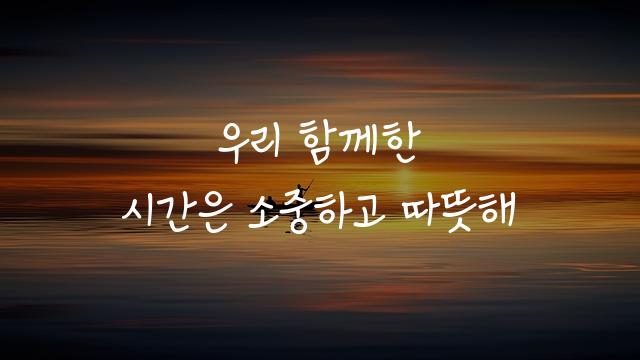
교보손글씨 2022 김혜남은 교보문고에서 제작한 어른 손글씨 폰트로, 세련되고 친근한 인상을 주는 디자인입니다. 이 폰트는 전통적인 손글씨의 감성을 현대적으로 재해석한 특징을 가지고 있습니다.
교보손글씨 2022 김혜남은(는)
손글씨, 감성적인, 부드러움 계열의 생김새를 가지고 있으며
초대장, 인사말 카드, 일기/편지 등에서 자주 활용되며, 효과적인 메시지 전달에 적합합니다.
이 폰트는 교육, 크리에이티브, 문화/예술 분야에 잘 어울리며,
따뜻한, 감성적인, 편안한 느낌을 담고 있는 것이 특징입니다.